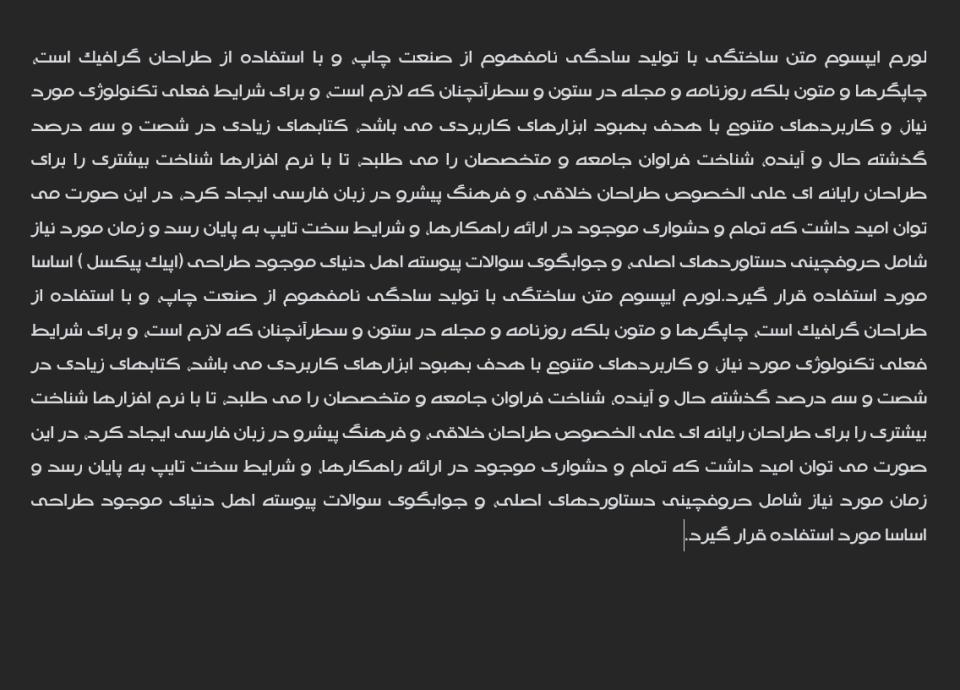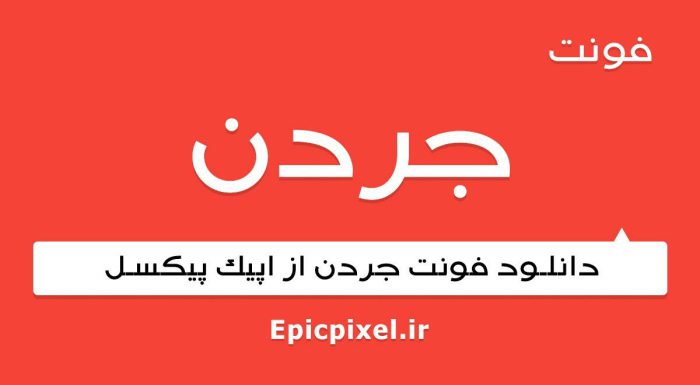
2 فونت جردن فارسی
فونت فارسی جردن، با طراحی مدرن و خوانا، انتخابی ایده آل برای طراحانی است که به دنبال ترکیبی از زیبایی و کارایی هستند. این فونت که به صورت رایگان ارائه می شود، در دو وزن معمولی Mj , MRT طراحی شده تا در پروژه های مختلف، از طراحی رابط کاربری گرفته تا تایپ متون طولانی، به راحتی قابل استفاده باشد.
یکی از ویژگی های برجسته فونت جردن، طراحی سنس سریف آن است که ظاهری مدرن و مینیمال به آن بخشیده و خوانایی آن را در اندازه های مختلف، به ویژه در صفحات وب و اپلیکیشن ها، تضمین می کند. این فونت با پشتیبانی از فرمت ttf، به راحتی در تمامی نرم افزارها قابل نصب و استفاده است و به طراحان این امکان را می دهد که بدون هیچ محدودیتی، خلاقیت خود را در پروژه هایشان به کار گیرند.
اگر به دنبال فونتی هستید که همزمان زیبایی، خوانایی و کارایی را در کنار رایگان بودن ارائه دهد، فونت فارسی جردن گزینه ای بی نظیر برای شما خواهد بود. این فونت با طراحی حرفه ای و ویژگی های منحصر به فرد خود، به پروژه های شما جلوه ای خاص می بخشد و تجربه کاربری بهتری را برای مخاطبانتان فراهم می کند.